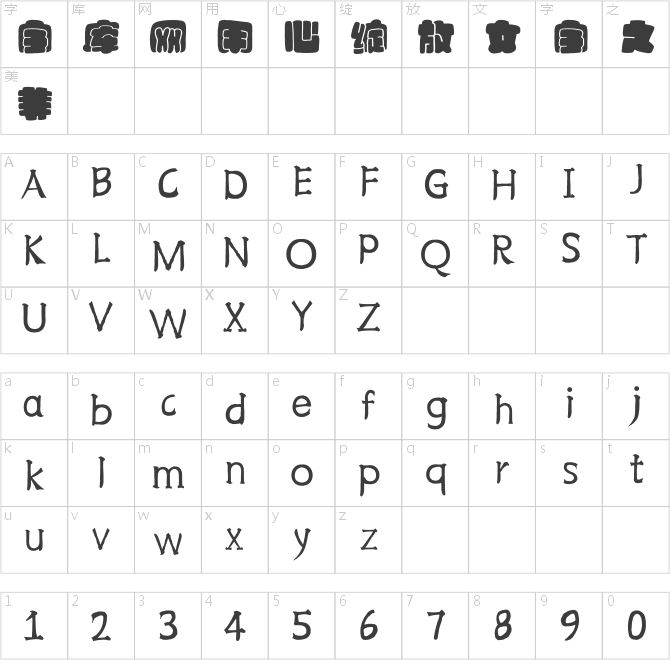
字体名称: 邯郸窝窝简体
邯郸窝窝简体
邯郸窝窝简体介绍
作品的独特性:邯郸窝窝简体以韩绍杰老师创作的电脑美术字制作而成。
主要特征该字体笔画粗壮,两端呈圆头,笔画相交紧密,呈凹陷窝状,中宫比较紧凑。黑字面大,字型粗旷,结构严谨,重心一致;笔划制作精良,线条刚柔相济,简洁有力。阅读舒适流畅,适用于报刊、杂志和书籍中的大型标题。
主要特点:邯郸窝窝简体,笔画粗状、横清晰、突出醒目等特点, 有着非常烈的